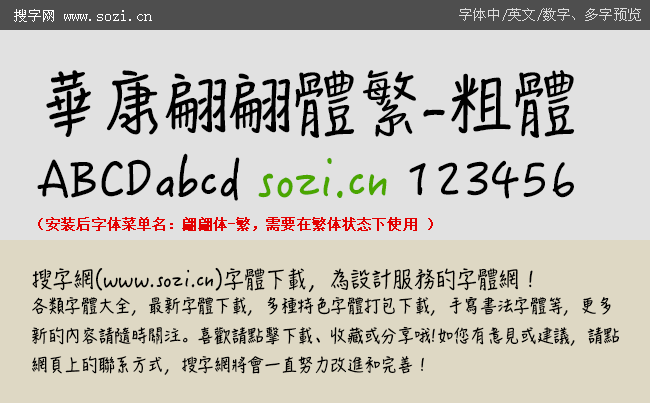
華康翩翩體繁-粗體
搜字網(wǎng)提供一款手寫(xiě)風(fēng)格的華康翩翩體中文字體下載。華康翩翩體是一款硬筆風(fēng)格的書(shū)法字體,字呈長(zhǎng)型,右上揚(yáng)起,清秀灑脫,筆觸帶著俏皮的律動(dòng)感,整體活潑生動(dòng),呈現(xiàn)自然手感,是一套親和隨興的手寫(xiě)字體。適用于海報(bào)設(shè)計(jì)、包裝設(shè)計(jì)、網(wǎng)頁(yè)設(shè)計(jì)等廣告設(shè)計(jì)場(chǎng)合。